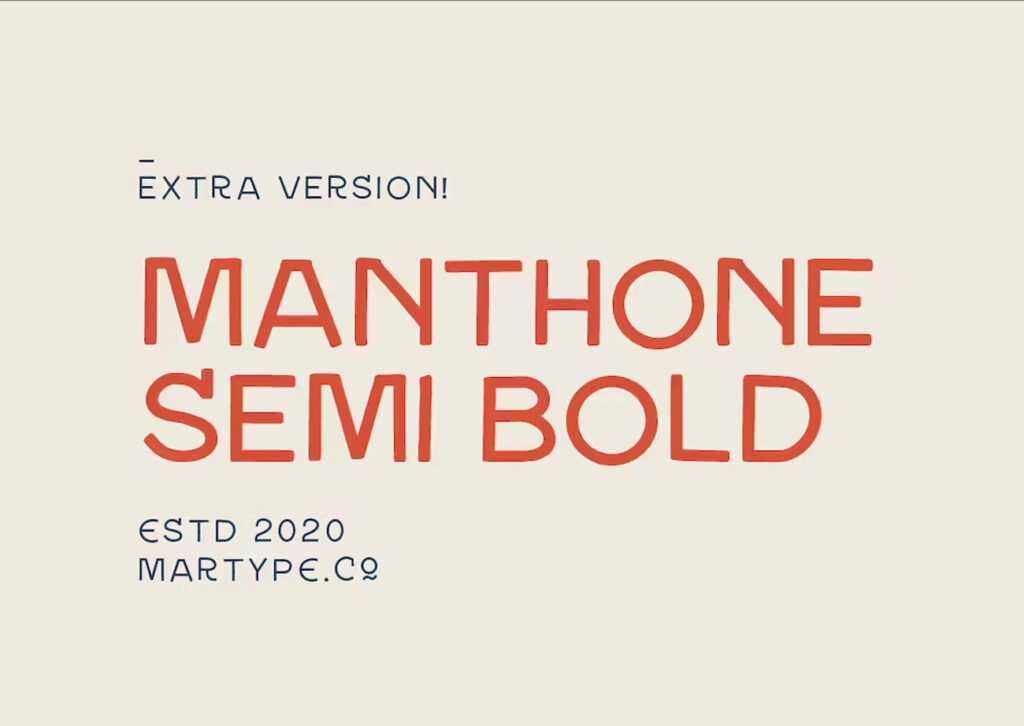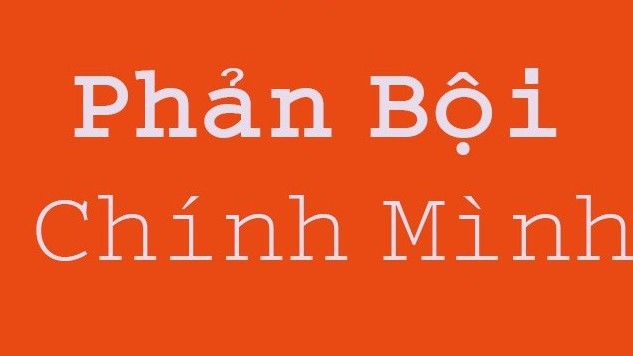
Font chữ chân phương là nhóm phông chữ sở hữu đường nét ngay ngắn, tỷ lệ chuẩn mực và loại bỏ hoàn toàn các chi tiết hoa mỹ hay uốn lượn phức tạp. Đại diện cho sự giản dị, khiêm nhường và tính chân thật, phông chữ chân phương là chất liệu trực quan tuyệt vời để các kiến trúc sư, kỹ sư trình bày các bản thuyết minh dự án nhà lắp ghép cộng đồng, tài liệu kỹ thuật vật liệu hay biển chỉ dẫn tại các khu nhà vườn sinh thái.
Sự thuần khiết không cầu kỳ và khả năng truyền tải thông tin của font chữ chân phương
Điểm cuốn hút của font chữ chân phương nằm ở tính dễ tiếp nhận và sự thân thiện đối với mắt người đọc ở mọi lứa tuổi. Cấu trúc chữ sở hữu độ dày nét đồng đều hoặc có độ chuyển tiếp nhẹ nhàng, các góc cạnh được bo gọn tinh tế gợi nhớ đến những trang sách giáo khoa hay những bức thư tay nắn nót thuở học trò.
Sự ổn định về mặt thị giác của dòng font này giúp truyền tải thông tin một cách chân thành, minh bạch và không khoa trương. Khi kết hợp cùng các vật liệu kiến trúc mộc mạc như tường gạch không trát, vách gỗ thông tự nhiên, cột bê tông trần hay tấm panel phẳng trong các công trình module, font chân phương tạo nên sự hòa quyện thẩm mỹ trầm tĩnh.
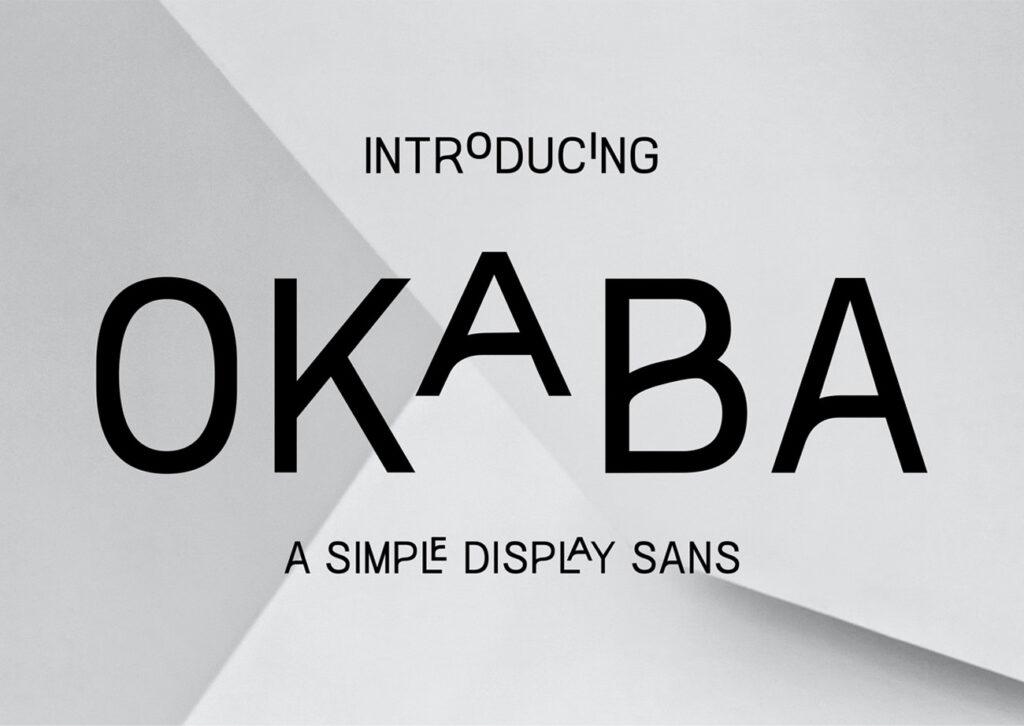
| Phân loại phong cách | Humanist Sans / Plain Serif / Textbook / Honest Style |
| Mục đích phù hợp | Thuyết minh kỹ thuật, biển chỉ dẫn công cộng, giáo án |
Tư vấn từ chuyên viên: Font chân phương được đánh giá cao nhờ khả năng hiển thị rõ nét trên các khối văn bản dài. Để bản thiết kế đạt hiệu quả thẩm mỹ tốt, bạn nên sử dụng phông chữ này cho phần nội dung thuyết minh chi tiết hoặc bảng số liệu.
03 Ứng dụng font chân phương vào công trình thực tế
Nhờ vẻ ngoài đĩnh đạc và tính ứng dụng thực tế cao, bộ phông chữ này mang lại giá trị thực tế lớn trong khâu hoàn thiện các công trình kiến trúc giàu tính nhân văn:
- Hệ thống biển hiệu cho Trường học và Nhà sinh hoạt cộng đồng: Những nét chữ chân phương rất ăn ý khi gia công chữ nổi bằng gỗ mộc hoặc sơn trực tiếp lên vách tường vôi trắng, giúp các công trình nhà lắp ghép vùng cao toát lên vẻ trang nghiêm và ấm áp.
- Bảng chỉ dẫn và Sơ đồ thoát hiểm công trình: Phông chữ này khi in trên các tấm alu phẳng hoặc mica mờ sẽ giúp công nhân và cư dân dễ dàng nhận biết các lối thoát hiểm, vị trí bình cứu hỏa một cách nhanh chóng và chính xác.
- Thuyết minh giải pháp kiến trúc và Báo cáo nghiệm thu: Sử dụng phông chữ chân phương cho toàn bộ phần văn bản giải trình kỹ thuật giúp tập hồ sơ trông ngăn nắp, thể hiện sự minh bạch và tinh thần làm việc cẩn trọng của đơn vị thi công.
03 Lưu ý bố cục font chữ chân phương luôn trang nhã và dễ đọc
Để khai thác hiệu quả vẻ đẹp của dòng font mộc mạc này mà không gây cảm giác tẻ nhạt cho bản vẽ, người thiết kế nên lưu tâm một số kinh nghiệm sau:
- Cân đối khoảng cách dòng: Với cấu trúc ký tự chuẩn mực, bạn nên duy trì khoảng cách dòng ở mức vừa vặn (khoảng 1.3 – 1.4 lần cỡ chữ) để các dòng văn bản giữ được sự liên kết nhịp nhàng, tạo nhịp điệu đọc êm ái.
- Phân tầng nội dung bằng hệ thống biến thể: Hãy tận dụng biến thể Bold cho các đề mục và Regular cho phần nội dung mô tả, tránh dùng quá nhiều màu sắc khác nhau để giữ trọn vẹn vẻ trang nhã và nghiêm túc của trang tài liệu.
- Căn lề trái tự nhiên: Khác với các phông nghệ thuật, font chữ chân phương hiển thị rất đẹp mắt khi căn lề trái tự nhiên, tạo nên các đoạn văn bản có trật tự rõ ràng và gần gũi với thói quen thị giác của người đọc.